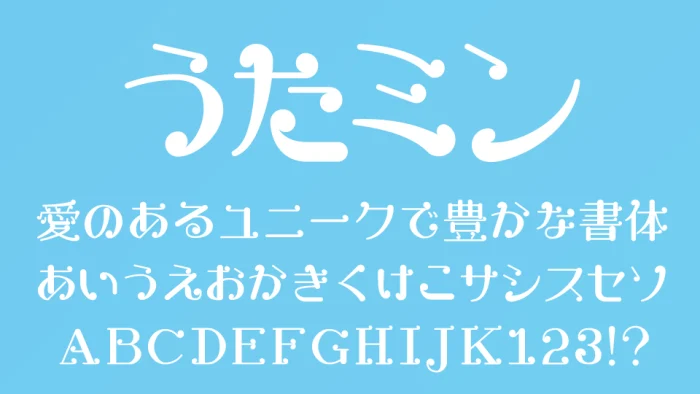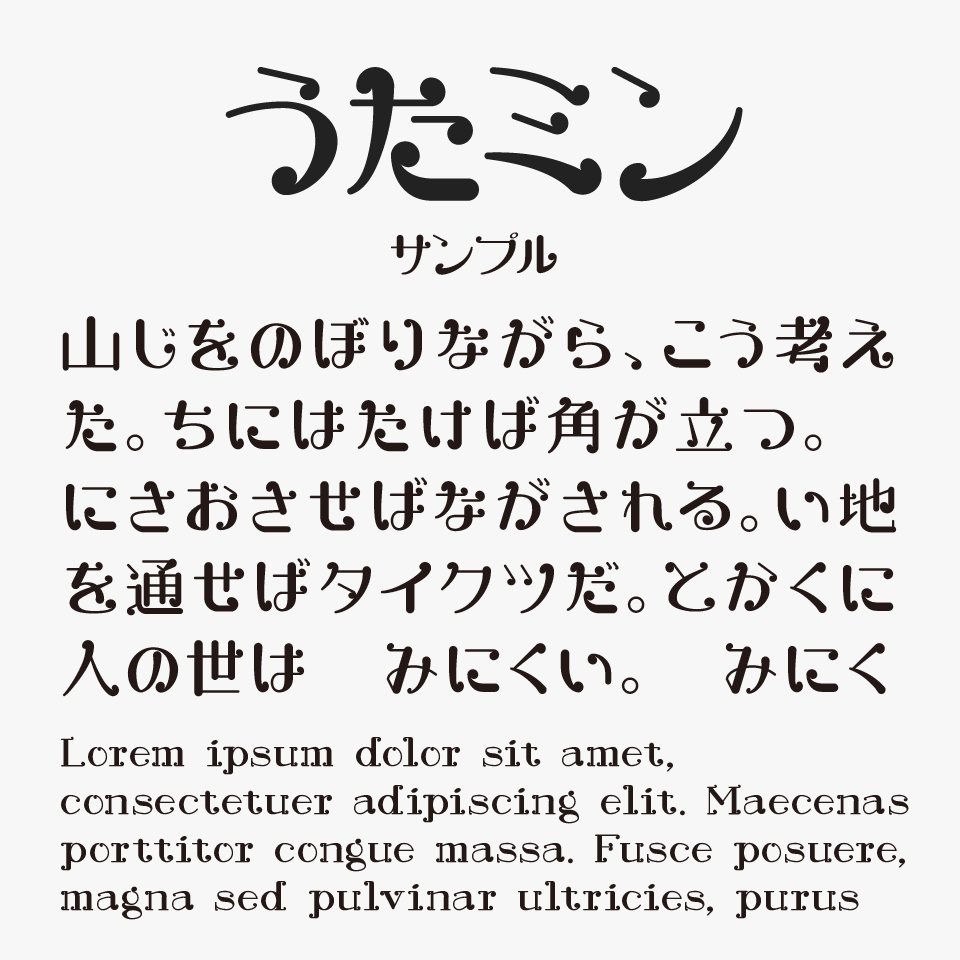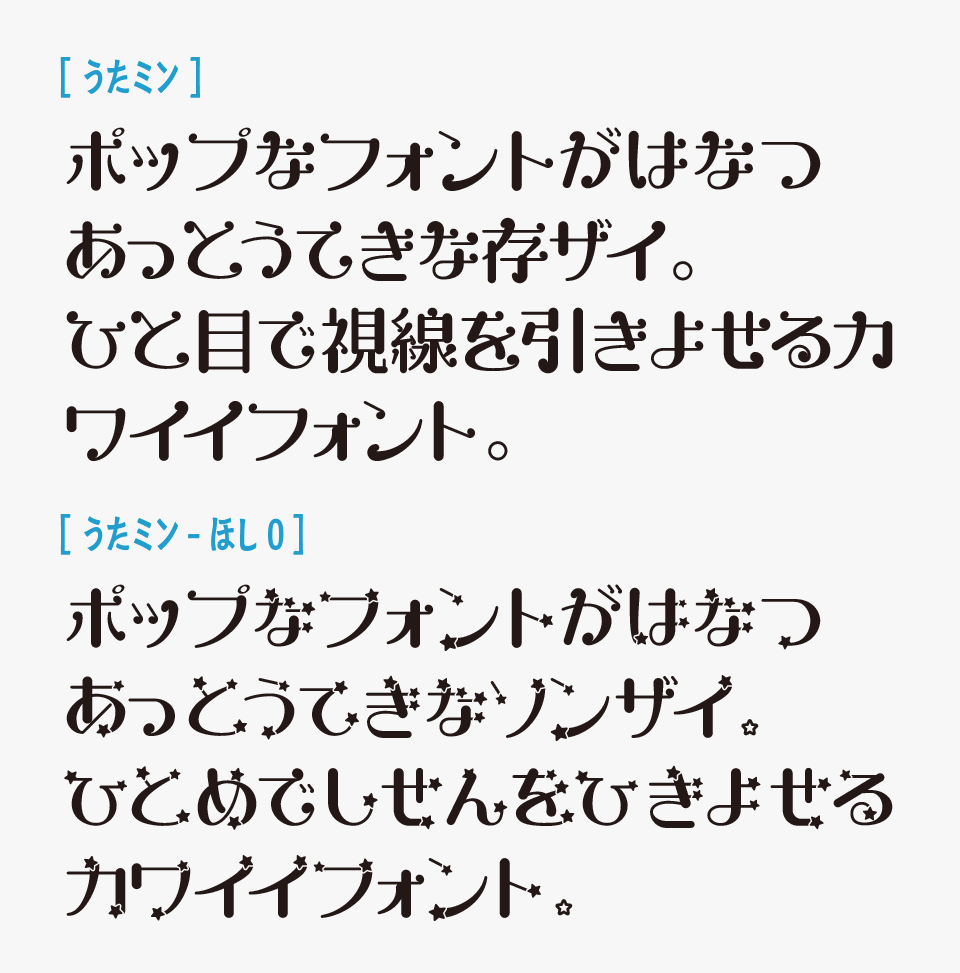
うたミンフォント
うたみんフォント
うたミンフォントは、歌う文字というコンセプトで作られてたフォントです。
歌う文字をコンセプトに音符のようなエレメントが文字の先端に装飾されているのがポップにも感じます。かつ明朝体ベースで作れられているので少しエレガントな雰囲気もあります。
収録文字は、ひらがな、カタカナ、全角数字、句読点、小学2年生分及び一部の漢字を収録されています。